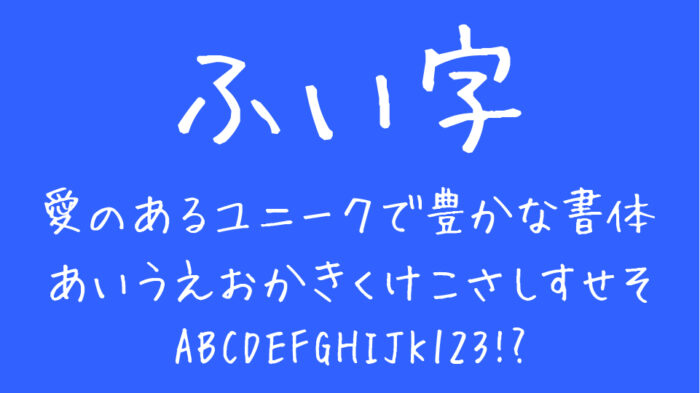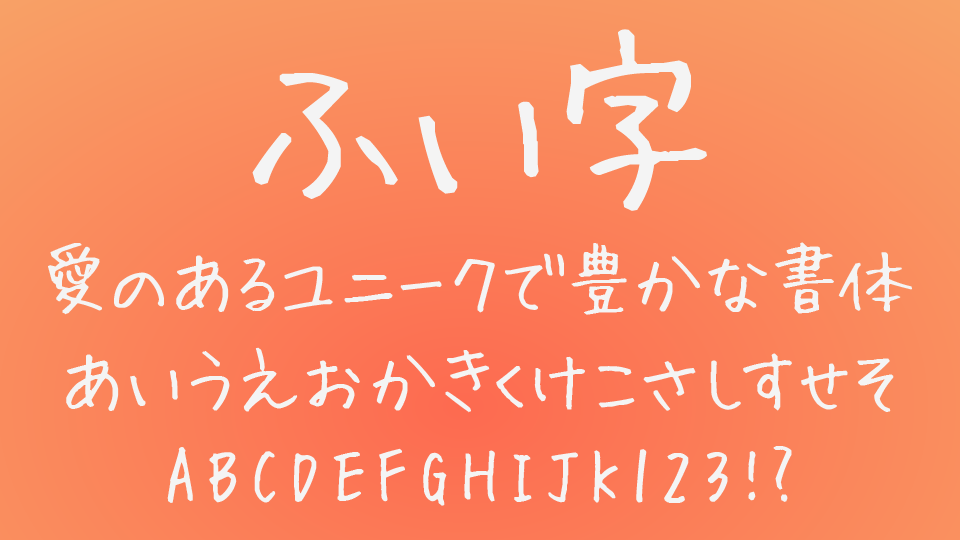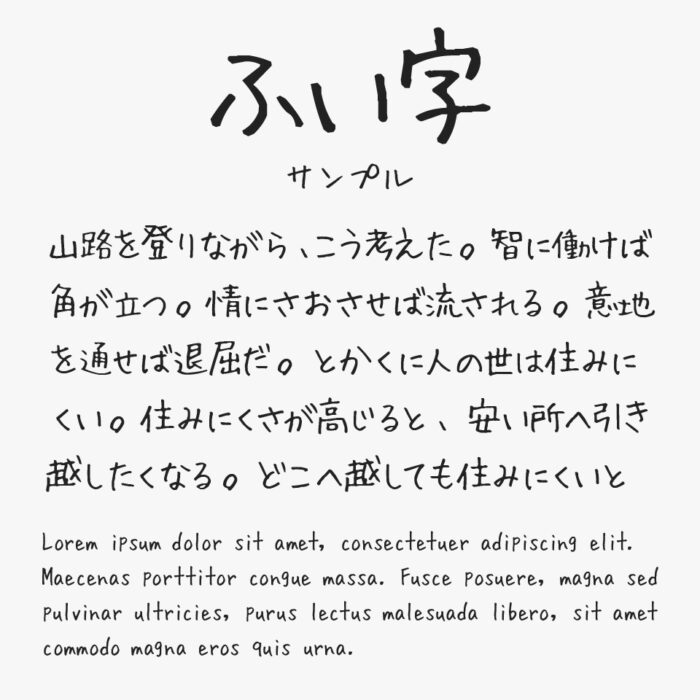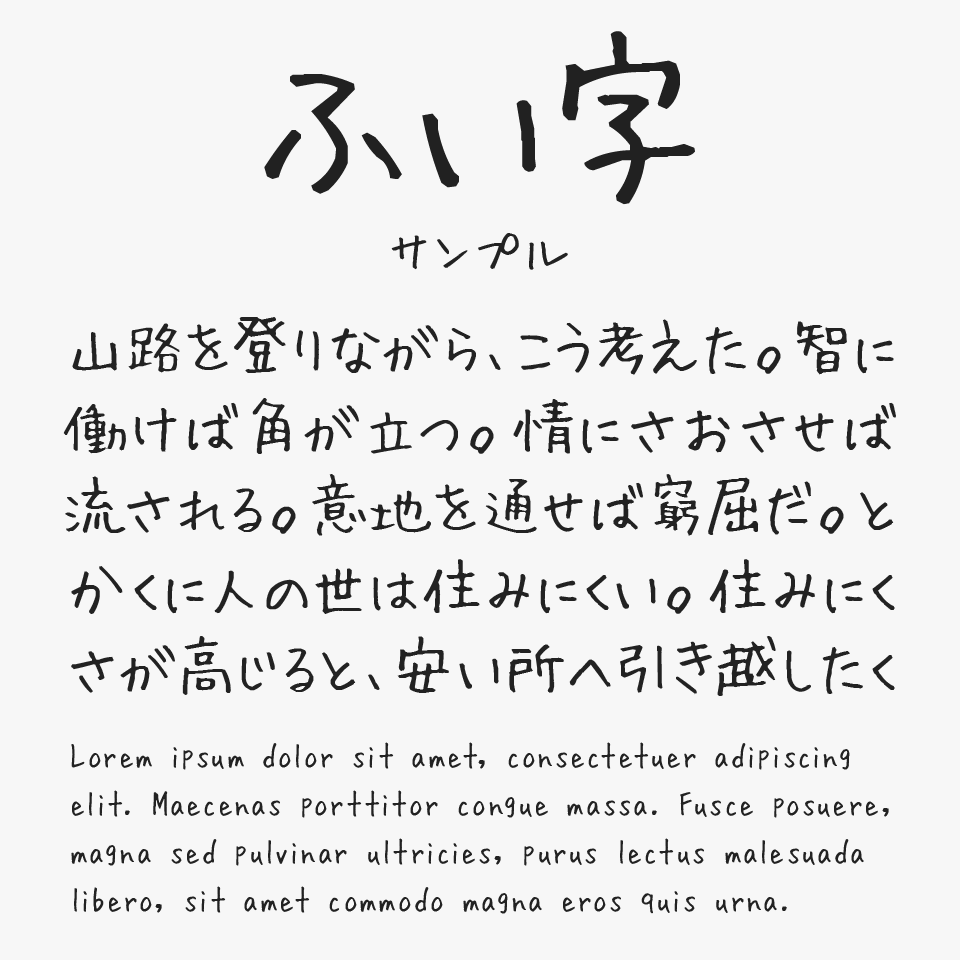
ふい字
ふい字フォントは、老舗の手書きフォント「ふい字置き場」を代表するやわらかく可愛らしい手書きフリーフォントです。
ボールペンで書いたかのような細線は、一定の太さになっているので、とっても幅広い場面に使いやすく、昔から人気のある手書きフォントの1つです。
女性的なやわらかい筆跡で、太さも細すぎず太すぎずちょうど良いラインの細さ可愛く汎用性が高い手書きフォントです。
ふい字
収録文字は、ひらがな・カタカナ・記号・英数字・漢字は第二水準まで収録されています。
通常の等幅タイプの「ふい字」と、文字毎に文字幅が調整されているプロポーショナルタイプの「ふい字P」の2種類があります。